王行满
王行满简介
王行满,高宗时人。工正书,事迹无考,生卒年月不详,官至门下录事。书法自欧虞出,秀逸柔婉,笔力丰满。河南省偃师市府店镇古招提寺的《大唐二帝圣教序石碑》即出自其手。此碑沈道元刻石,阳文篆额,碑文正书,高2.44米、宽1.04米,用笔端方绵密,绰有姿致。陕西醴泉县昭陵博物馆有《周护碑》,1974年出土于昭陵葬墓。碑文35行,行80 字,许敬宗撰。名家评议王行满此碑的书写“端庄秀润,于欧阳询、虞世南、褚遂良之外,自立风格”。传世作品还有《韩仲良碑》等。
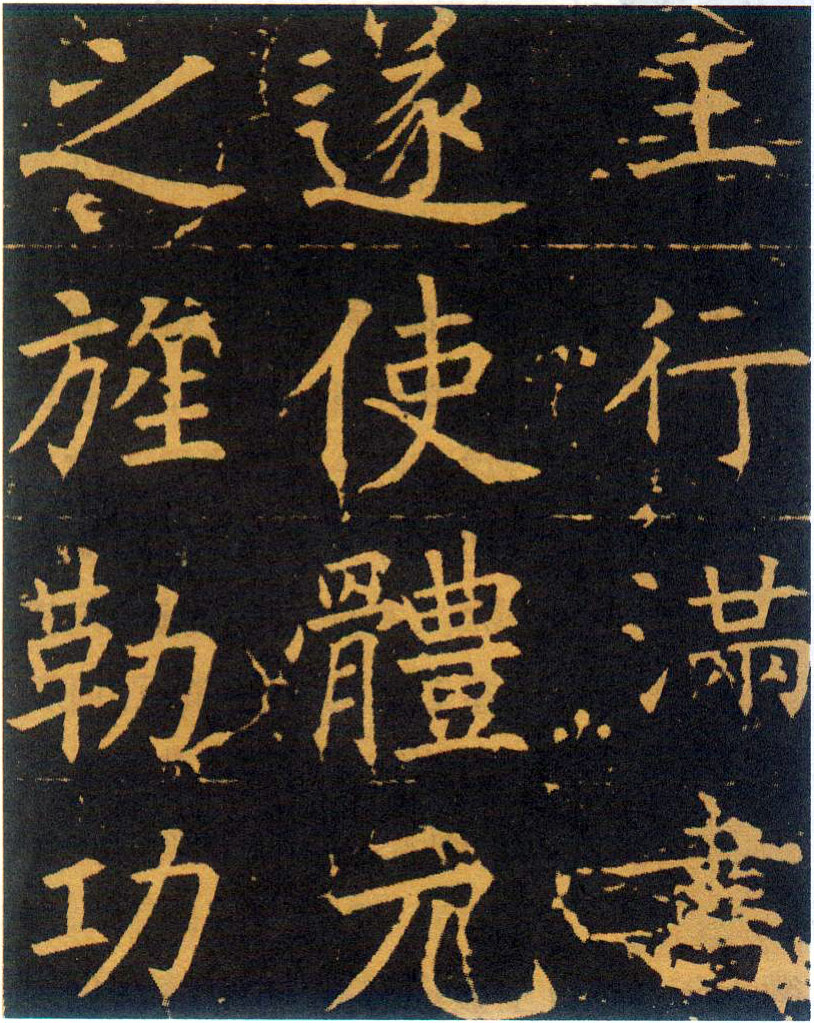
王行满《韩仲良碑》(局部)于志宁撰 唐永徽6年(655)3月14日立